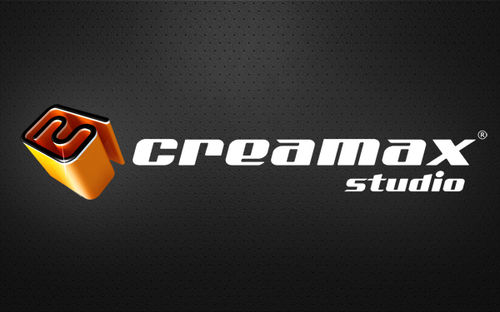
Есть знак. Какой шрифт лучше? Комментируем =)
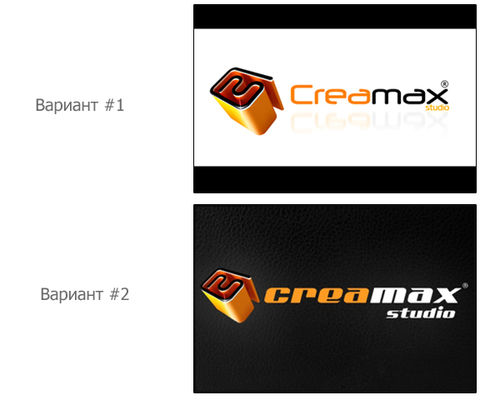
Два варианта написания.
Какой шрифт лучше и больше подходит к знаку - вариант №1 или вариант №2.
Ваши комменты плиз)
Шрифт больше в первом нравится.
ИМХО, Neuropol лучше)
Который день вы шрифт выбираете?
Вообще, я не спец по шрифтам, но у меня эти есть на компе... Может, лучше свой забацать?
Цитата ("Sasha_Aitken"):Вообще, я не спец по шрифтам, но у меня эти есть на компе... Может, лучше свой забацать?
Свой шрифт бацаеца очень и очень долго, но это при условии, если есть грамотный шрифтовик, если такового нет, лучше вообще за свои шрифт не браться, дело безнадежное абсолютно.
У "Амедиа" (вроде так пишется), это те, кто снимал "Моя прекрасная няня" и еще кучу сериалов на СТС знак точно такой же как и у вас, только буквы другие, если мне не изменяет память.
Первый конечно же лучше
Второй вариант. именно с одной частью оранжевой, а другой белой - так сразу отчетливо понятно из каких слов состоит название и лучше в память врезается
А мне первый больше понравился!